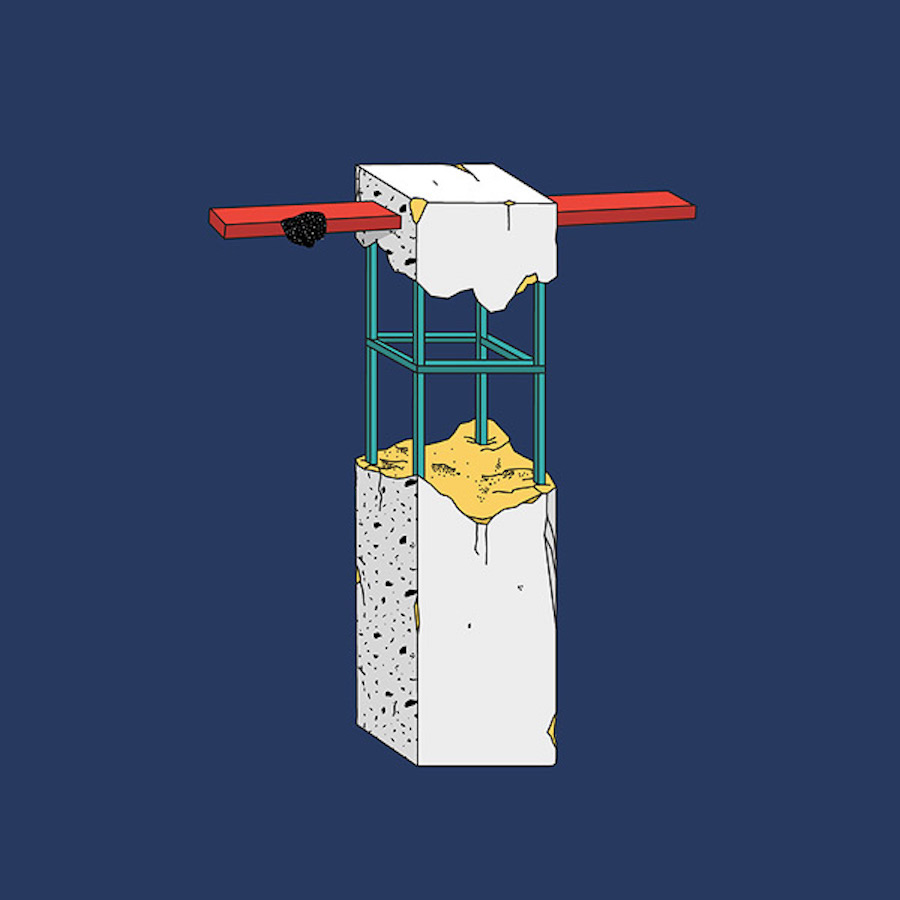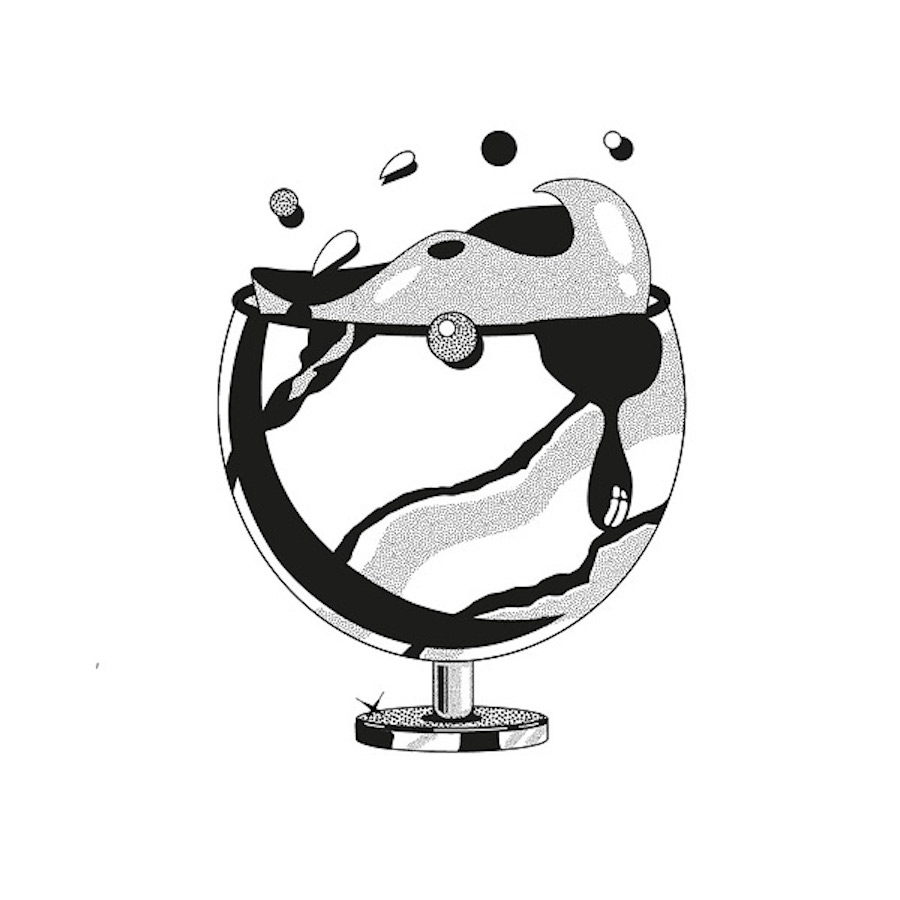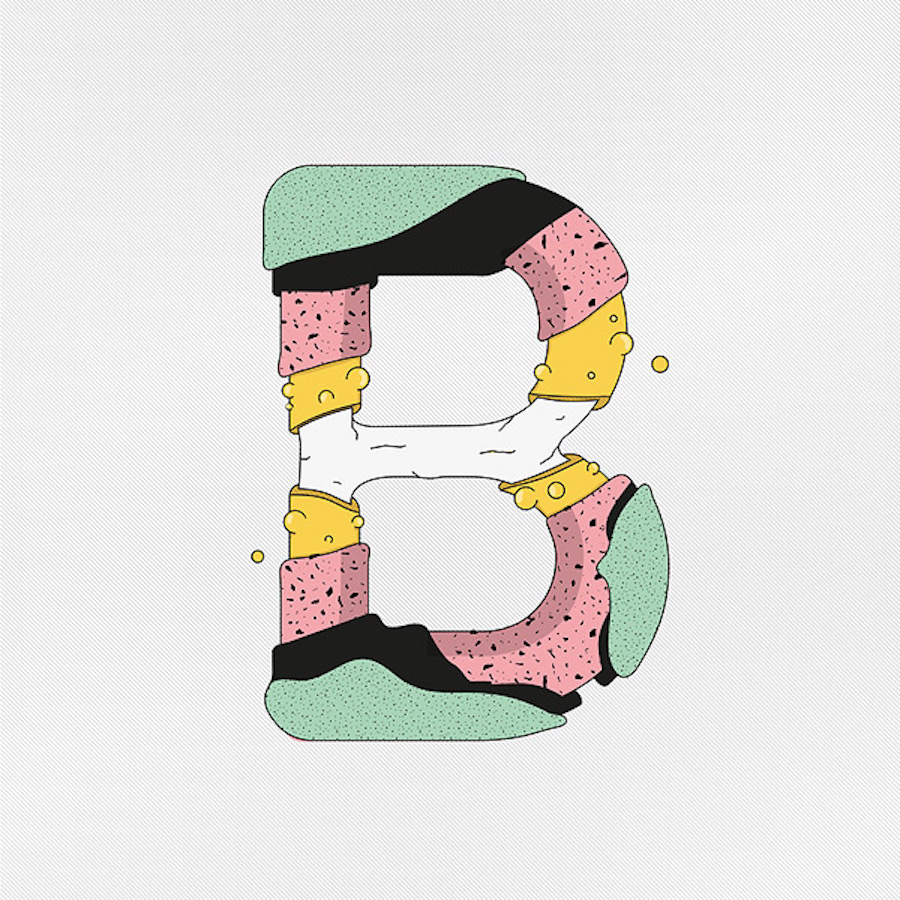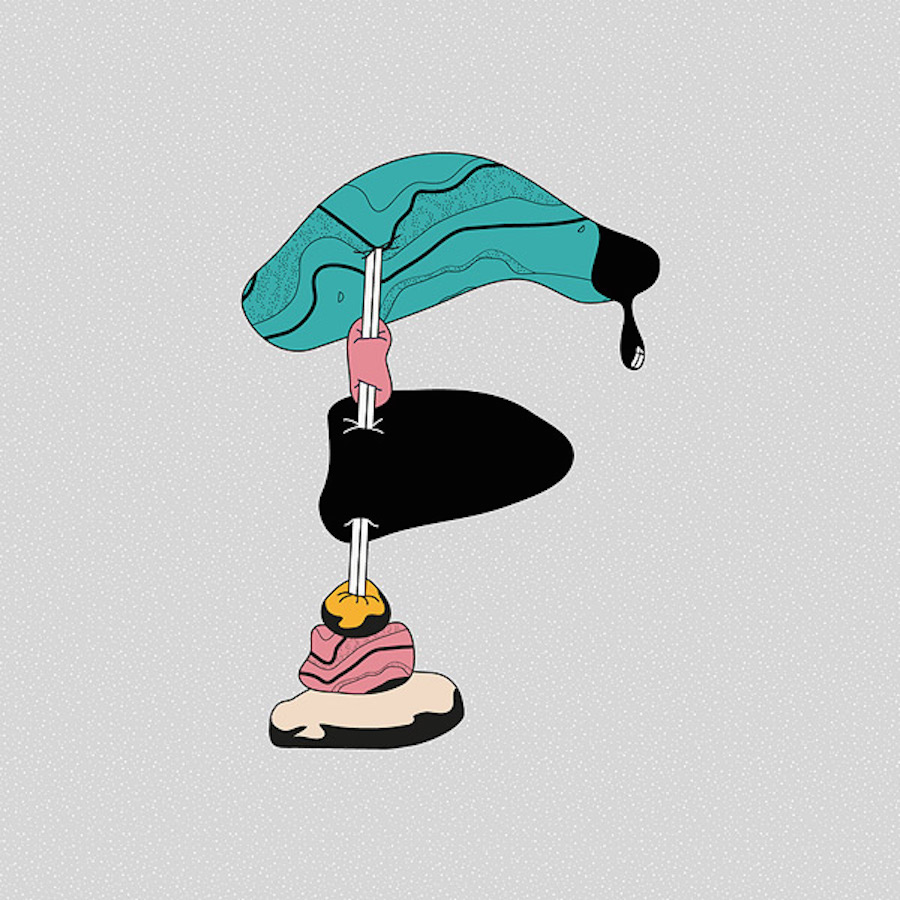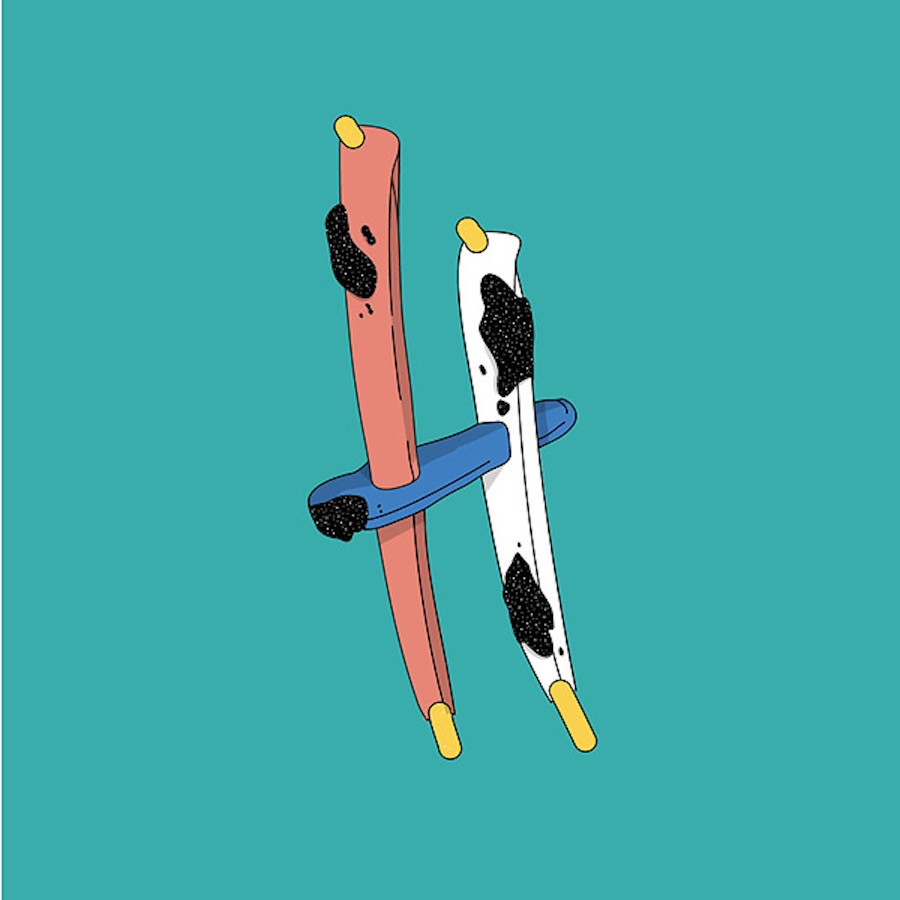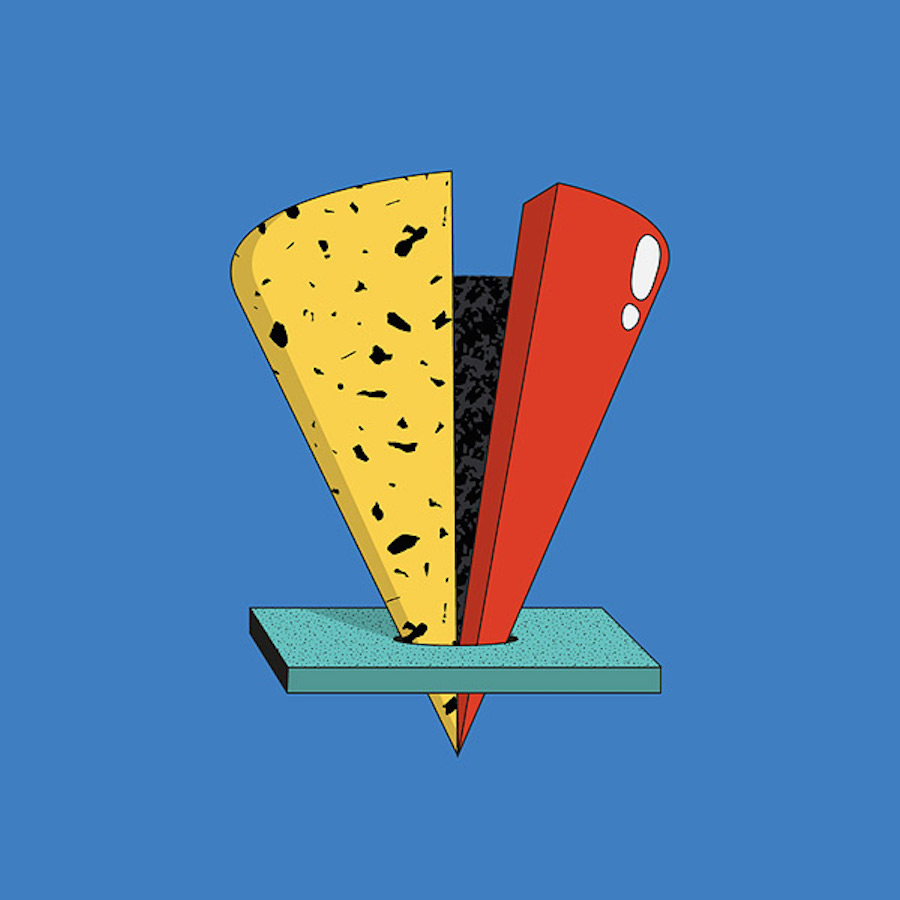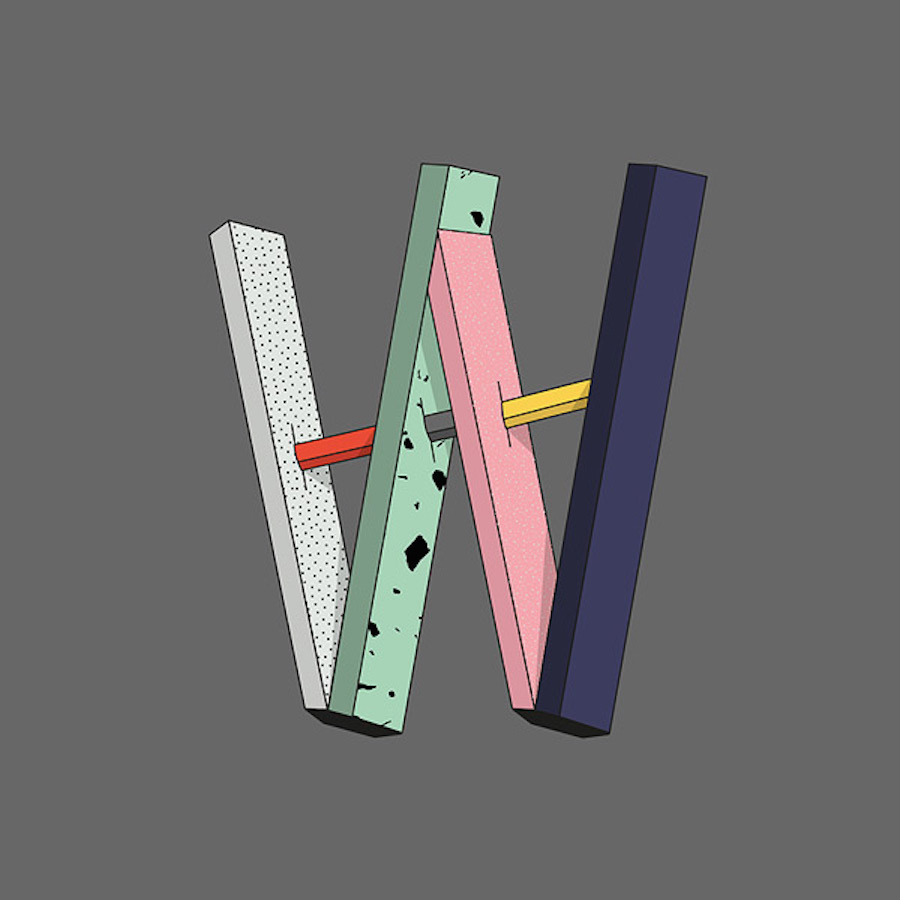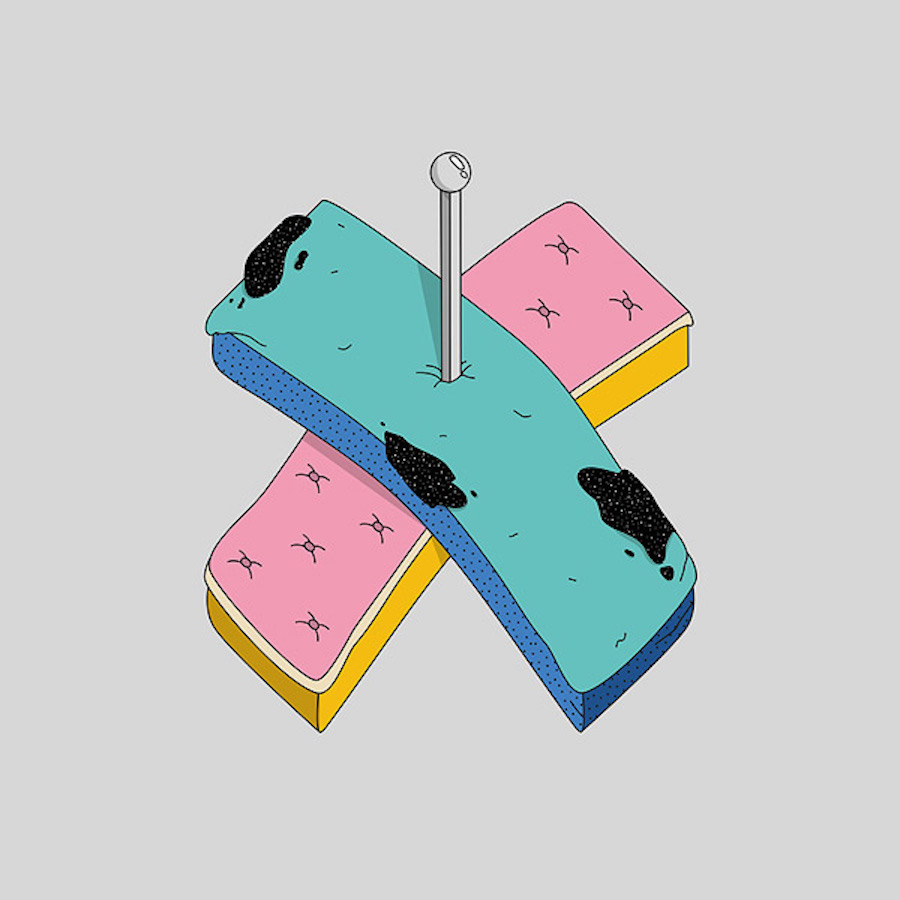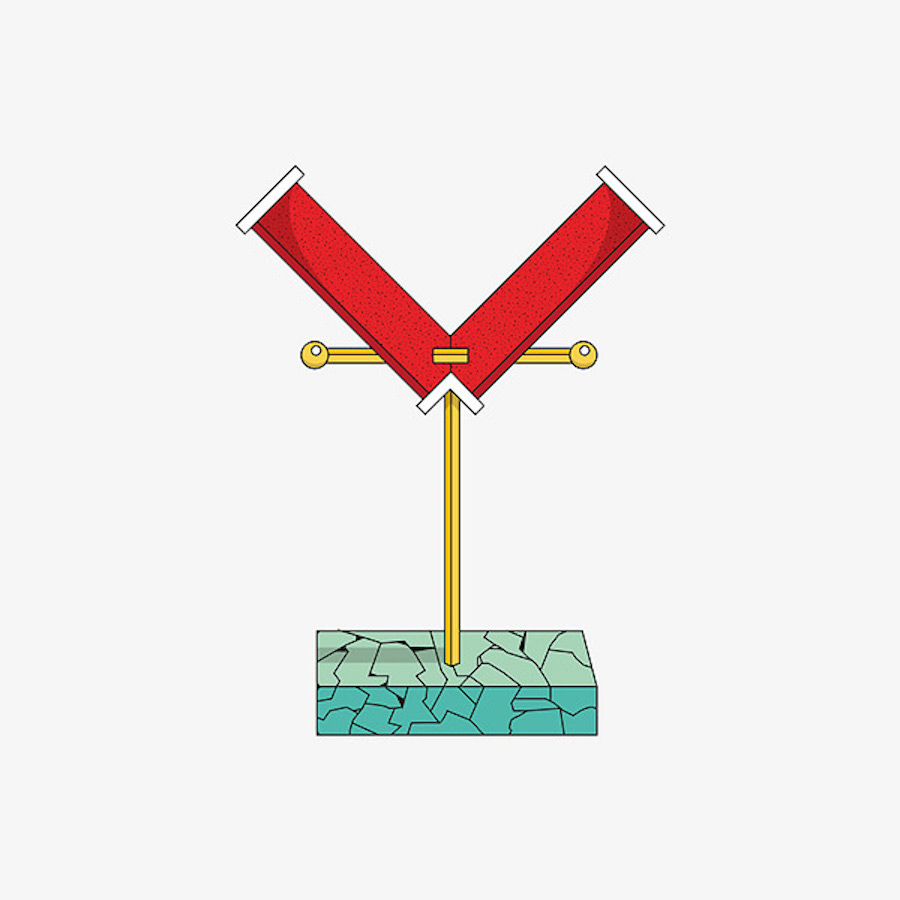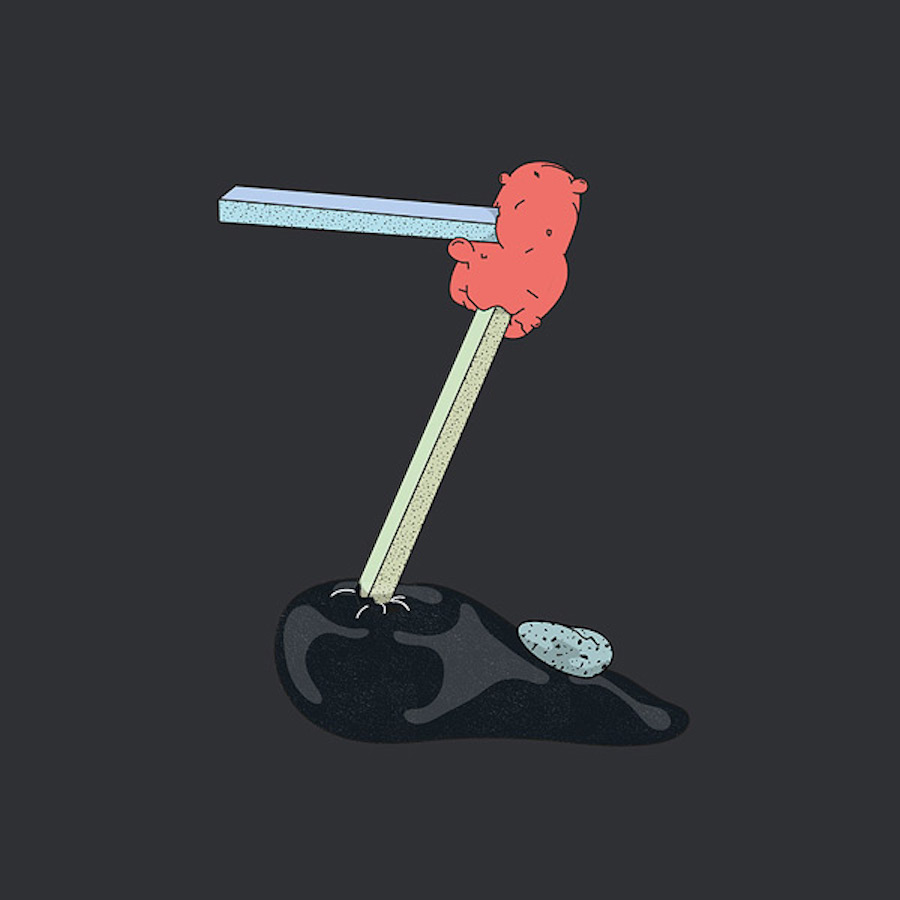
I colorati font dell’innovativo progetto tipografico di Mariano Pascual
È da Barcellona che Mariano Pascual ha realizzato  questo superbo lavoro di creazione di font per il progetto “36 Days of Type”, che invita diversi designer e illustratori a creare nuovi font durante un periodo di un mese.
Il prodotto della sua immaginazione è un originale alfabeto composto da diversi strati di oggetti incastrati tra di loro. Un modo creativo per dare freschezza al lavoro del font design.